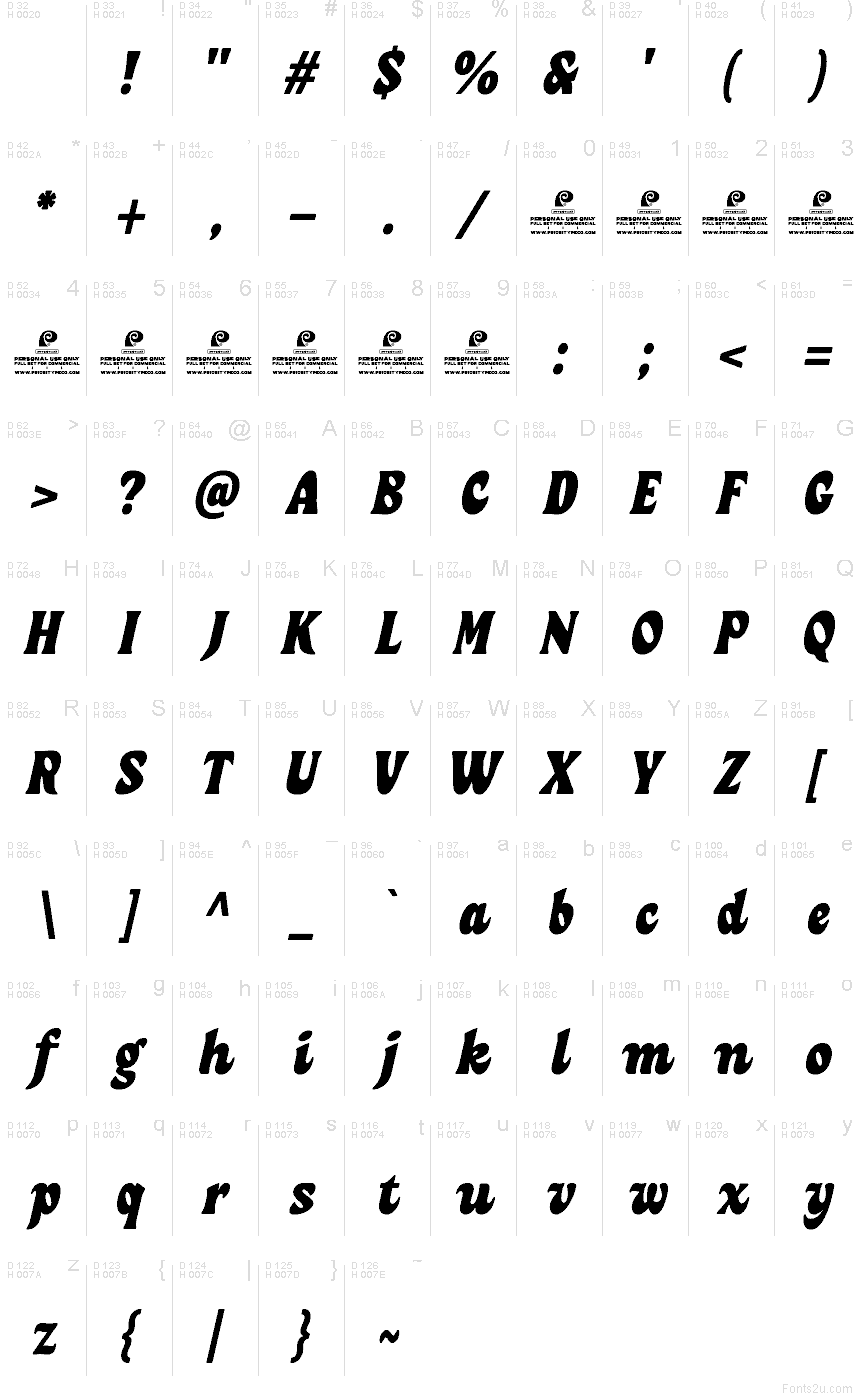
Ombre Nouveau, di Prioritype Co., è un font display retrò gratuito dal sapore Art Nouveau e un'estetica sontuosa, perfetta per i poster. Le lettere si inclinano in avanti con un ritmo fluido, caratterizzate da curve generose, giunture morbide e terminali a bulbo che rendono il lettering quasi sciropposo e teatrale, ben oltre il semplice corsivo.
È ideale per il branding di cocktail bar, packaging cosmetici, insegne di caffè, locandine musicali, copertine di riviste e titoli dove serve una frase breve che definisca l'atmosfera. Essendo un font gratuito, funziona alla grande anche per monogrammi o titoli d'effetto, poiché il tratto accentuato e lo spessore conferiscono anche a poche lettere una presenza ricca e dal sapore d'altri tempi.
Ombre Nouveau DEMO ExtBd